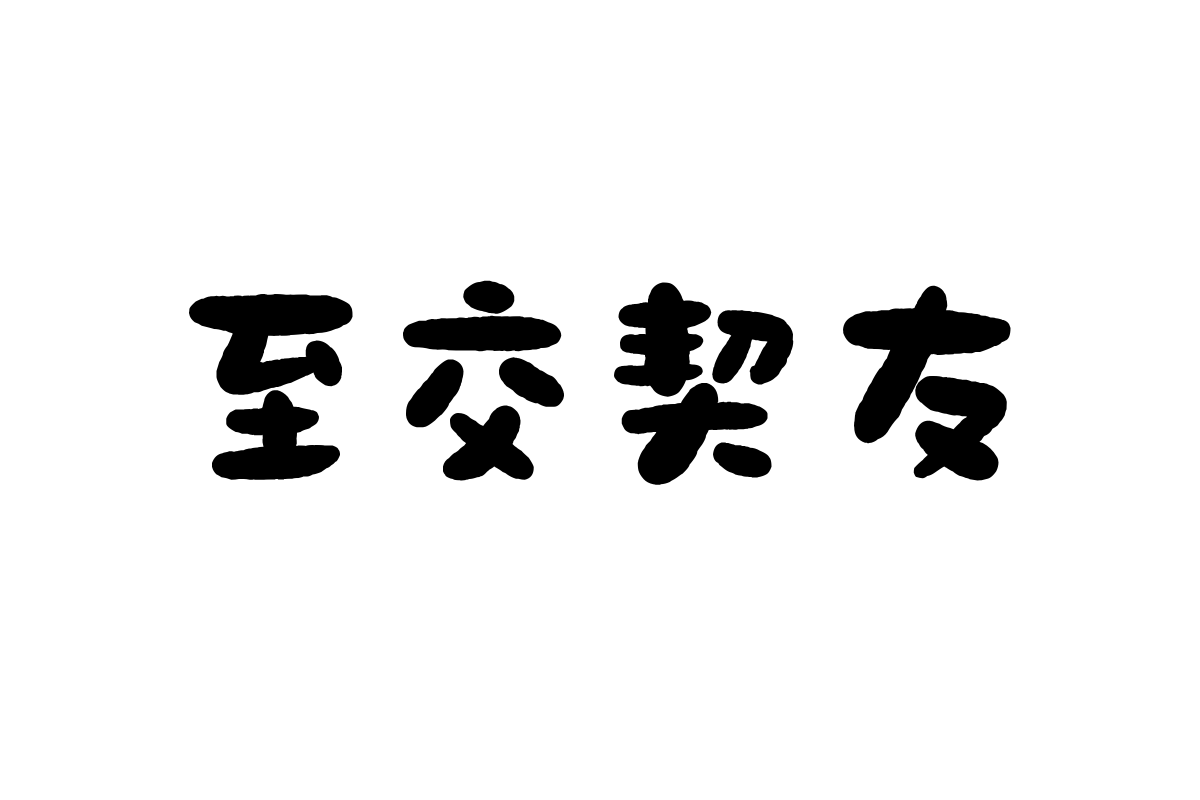
龚帆酸奶布丁体字体是一款具有现代感和时尚气息的中文字体。它由设计师龚帆设计,灵感来源于酸奶布丁这种美食,因此得名“酸奶布丁体”。
这款字体的特点是字形圆润可爱,线条流畅自然,给人一种轻松愉悦的感觉。它的笔画粗细适中,既有力度又不失柔美,适合用于各种文字设计,如标题、正文、广告等。
此外,龚帆酸奶布丁体字体还具有很好的可读性,无论是在印刷品还是电子屏幕上都能清晰展现。它的适用范围非常广泛,无论是儿童读物、青少年杂志还是成人商务文件,都能找到合适的使用场景。
总之,龚帆酸奶布丁体字体是一款非常适合现代审美的中文字体,无论是用于商业还是个人项目,都能展现出独特的魅力。